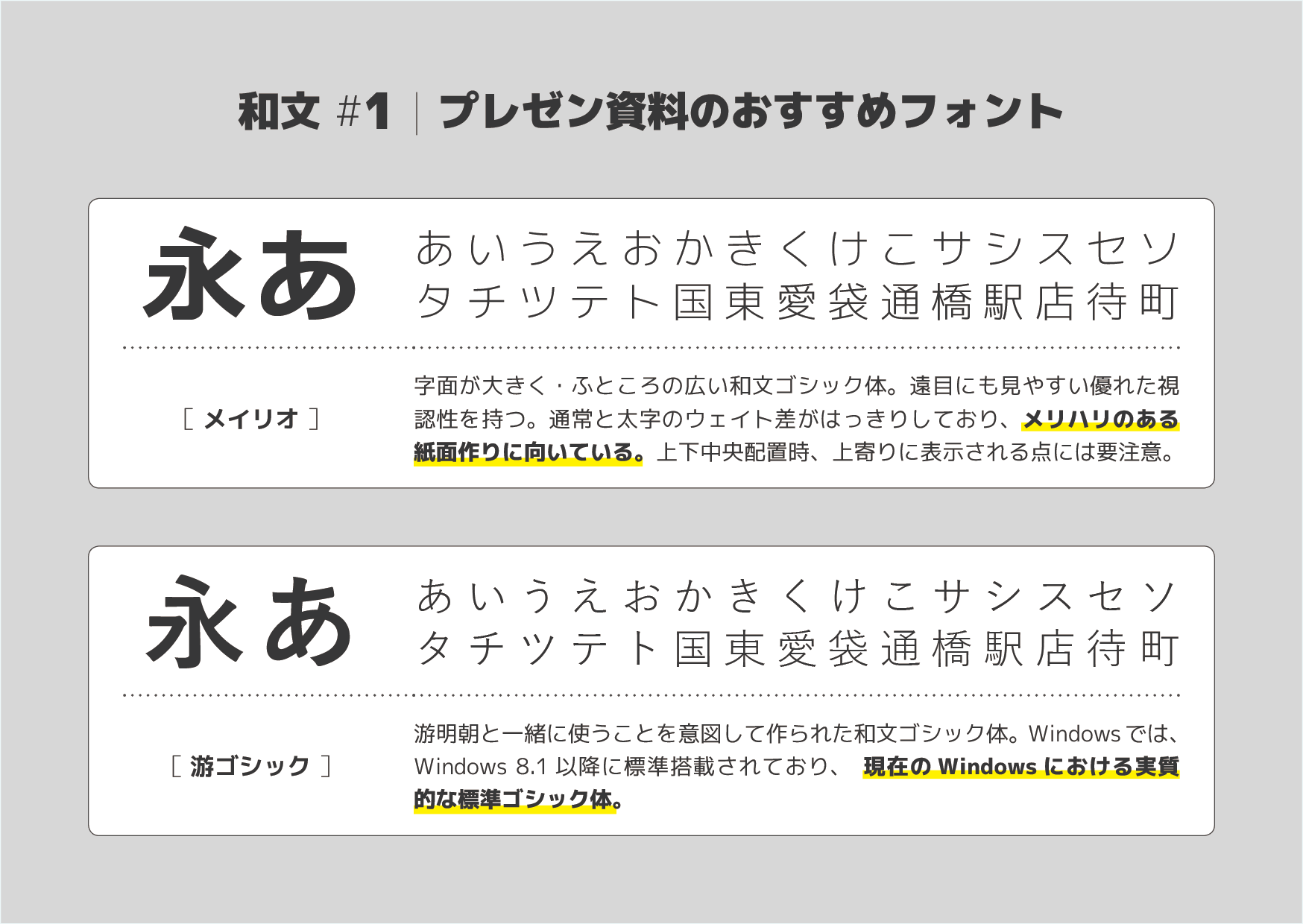
プレゼン フォント おすすめ
プレゼン フォント おすすめ. Google Fontsのサービスなど、最近では無料で使えるフォントも増えてきました。 しかし、数もかなり多くどんなフォントを使えばいいのか迷ってしまいますよね。 今回はWebデザインの現場からよく使う定番のフォントをご紹介いたします。 よく使う日本語フォント ゴシック体. どちらもそれぞれ特長があるわけだが、プレゼンのスライドで重要なのは、 可読性よりも可視性、判読性を重視した見やすいフォント選び だ。 そこで僕は、 ゴシック体(ヒラギノ角ゴ) をおすすめする。. 今回はこのような悩みを解決していきます。 結論から言います。 日本語⇒メイリオ 英語と数字⇒Segoe UI これで決まりです。終了! 詳しく説明していきますね。 本記事の内容 プレゼン資料の印象はフォントで激変する プレゼン資料にメイリオがおすすめな理由 英数字は「Segoe UI」を使って.
プレゼンノウハウ 文字の形が美しく視認性に優れており、欧文フォントの中では最もおすすめです。Windows OSに標準搭載されています。. 3 結局、PowerPointの文字って何ポイントがベストなん? 31 24ポイント以上が「誰でも見やすい」レベル.